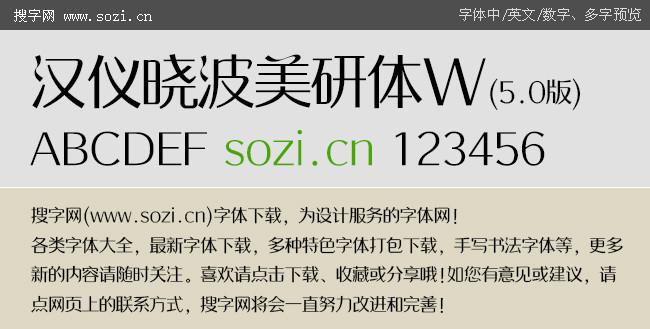
漢儀曉波美研體W5.0
搜字網(wǎng)提供一款漢儀曉波美研體W5.0字體下載,漢儀曉波美研體是一款漂亮的藝術(shù)字體。由漢儀曉波工作室出品,漢儀曉波美妍體是一款非常秀美的女性字體,筆形單薄清爽,有大量書寫的連筆處理,其中又克制不顯夸張,因而優(yōu)雅動人,適用于多種女性行業(yè)的設(shè)計應(yīng)用。(本字體為個人非商用版,如需要商用請聯(lián)系漢儀公司購買版權(quán))